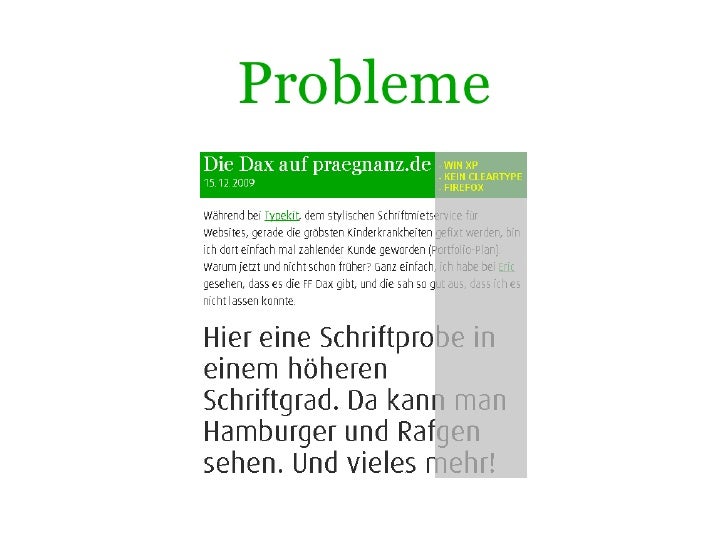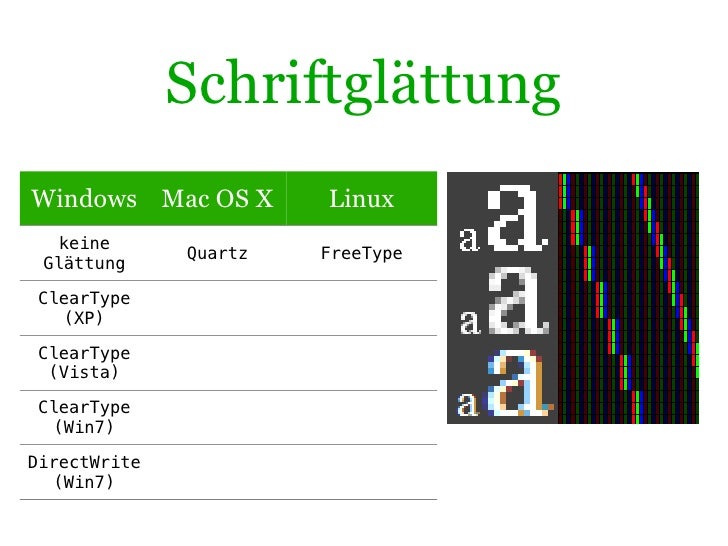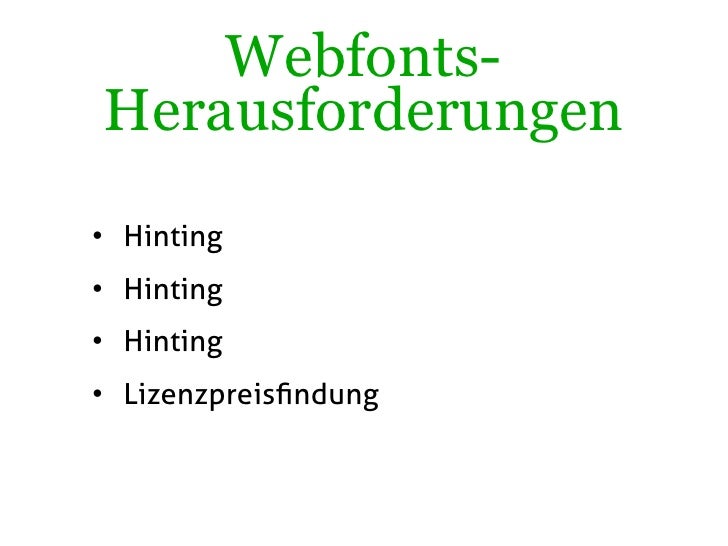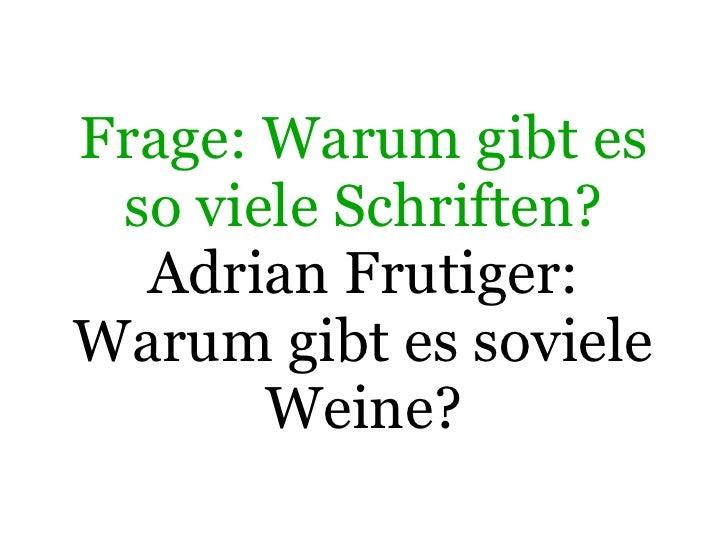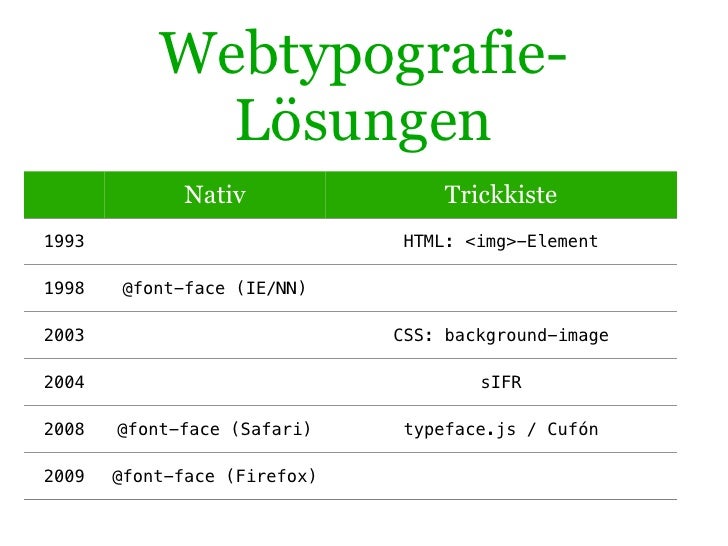
Webfonts im Jahr 2010
Vortrag von Gerrit van Aaken am Webmontag Würzburg
Webfonts im Jahr 2010
1. 1. Webfonts im Jahr 2010 Stand der Dinge von Gerrit van Aaken 18.1.2010 / Webmontag Würzburg
3. 3. Frage: Warum gibt es so viele Schriften? Adrian Frutiger: Warum gibt es soviele Weine?
4. 4. Verdana Times New Roman Das Problem Georgia Arial Courier
5. 5. Webtypografie- Lösungen Nativ Trickkiste 1993 HTML: <img>-Element 1998 @font-face (IE/NN) 2003 CSS: background-image 2004 sIFR 2008 @font-face (Safari) typeface.js / Cufón 2009 @font-face (Firefox)
6. 6. Synonyme für Native Font-Unterstützung • Webfonts • @font-face • Font-Linking / (Font-Embedding)
9. 9. 2009 ging’s los
10. 10. 2010 geht’s weiter Print Office Web
11. 11. Probleme
12. 12. Schriftglättung Windows Mac OS X Linux keine Quartz FreeType Glättung ClearType (XP) ClearType (Vista) ClearType (Win7) DirectWrite (Win7)
13. 13. Webfonts- Herausforderungen • Hinting • Lizenzpreisfindung